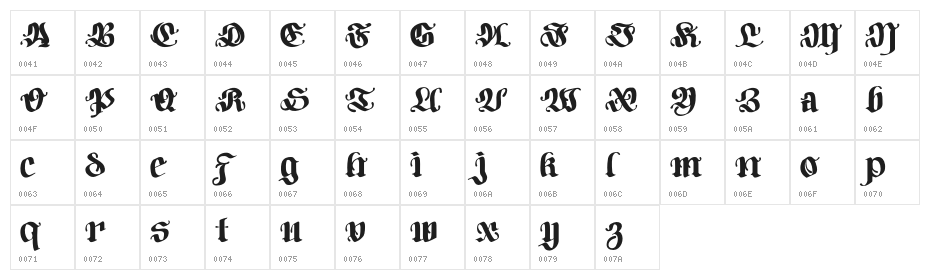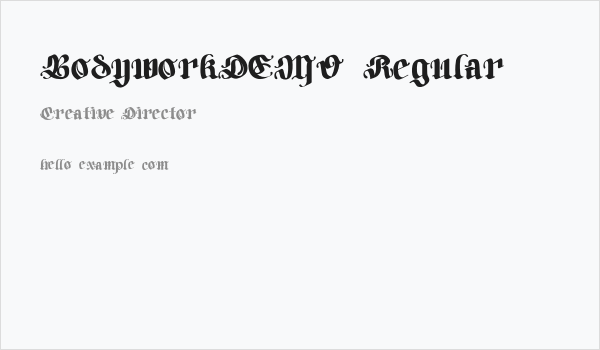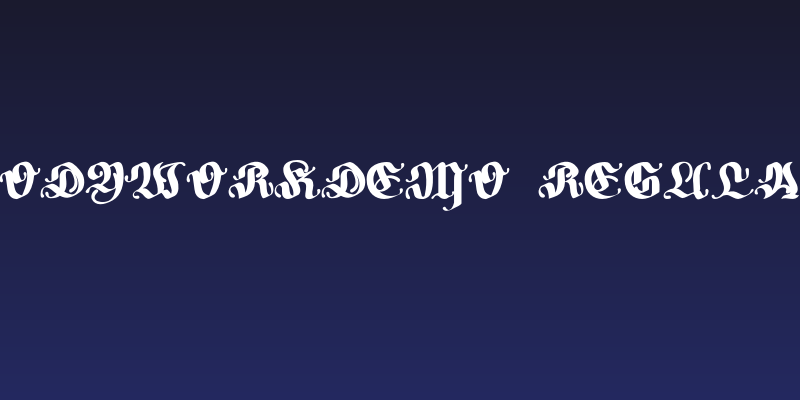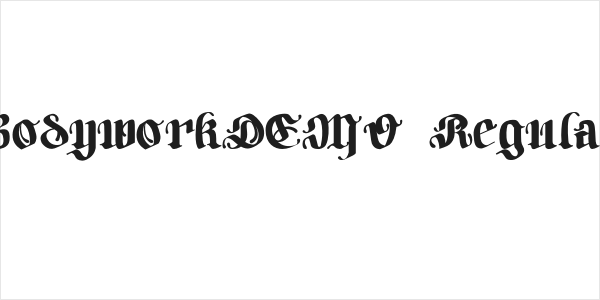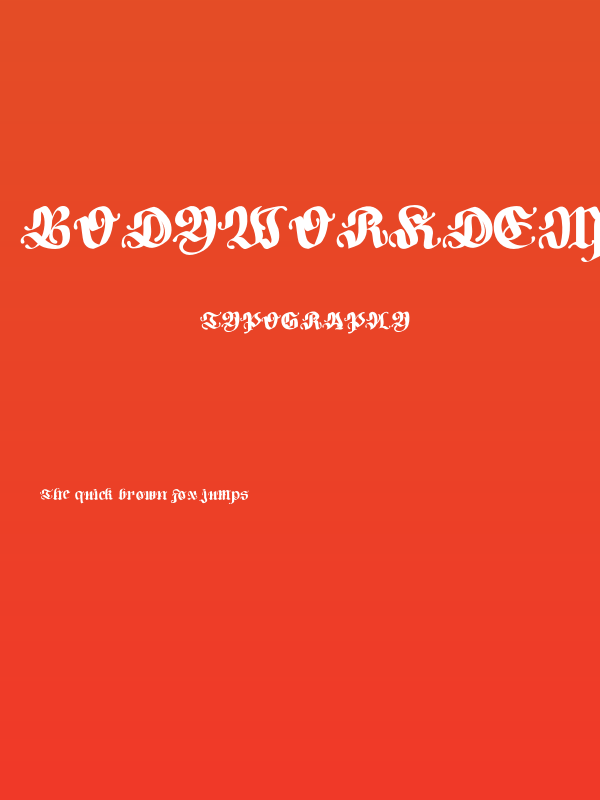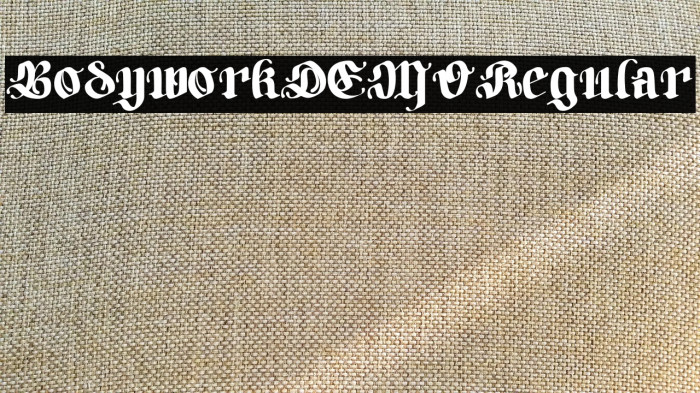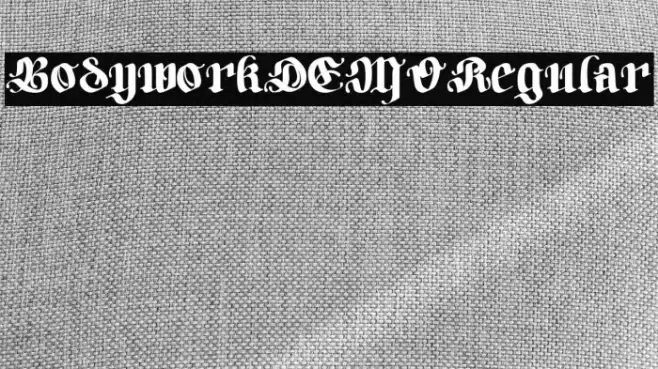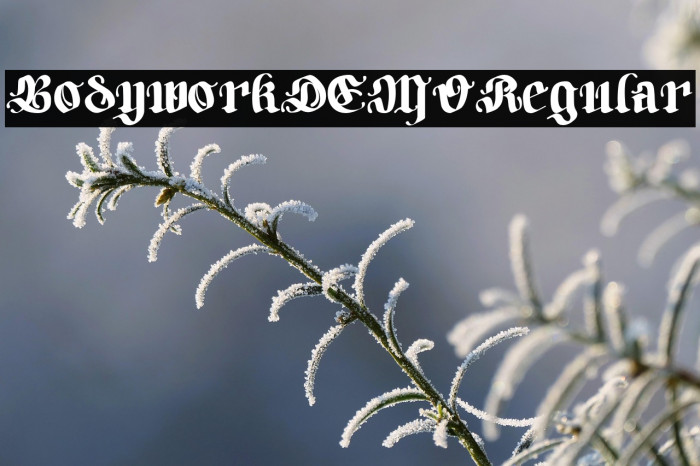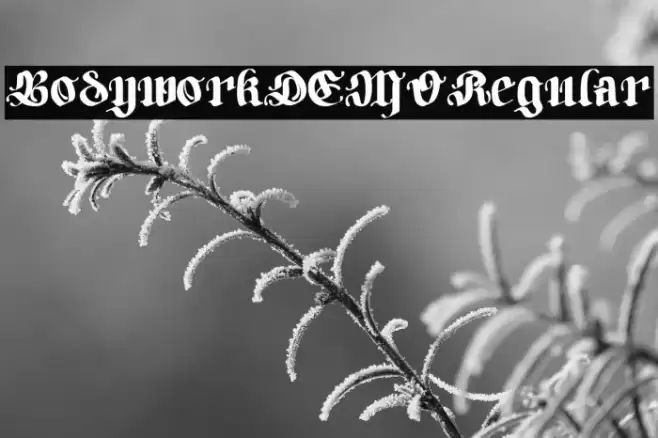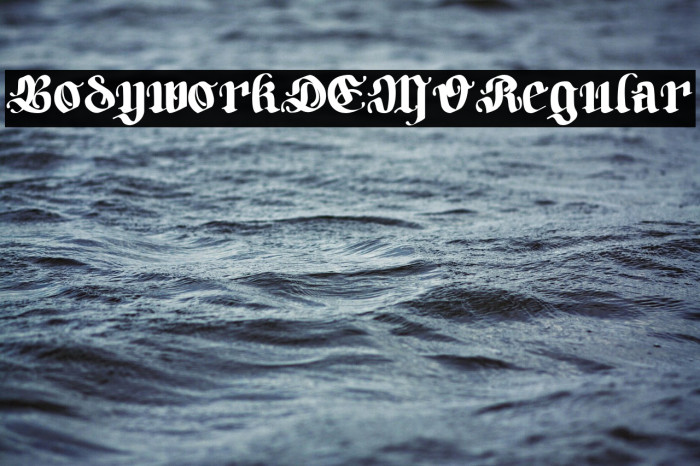
BodyworkDEMO-Regular Font
✎ Gothic
| Categorías | Gothic |
| Estilo general | Vintage |
| Caso de uso | Logos, Headlines, Decorative text |
| Proyectos propuestos | Suitable for vintage-themed designs, book covers, posters, and branding that requires a classic and elegant touch. |